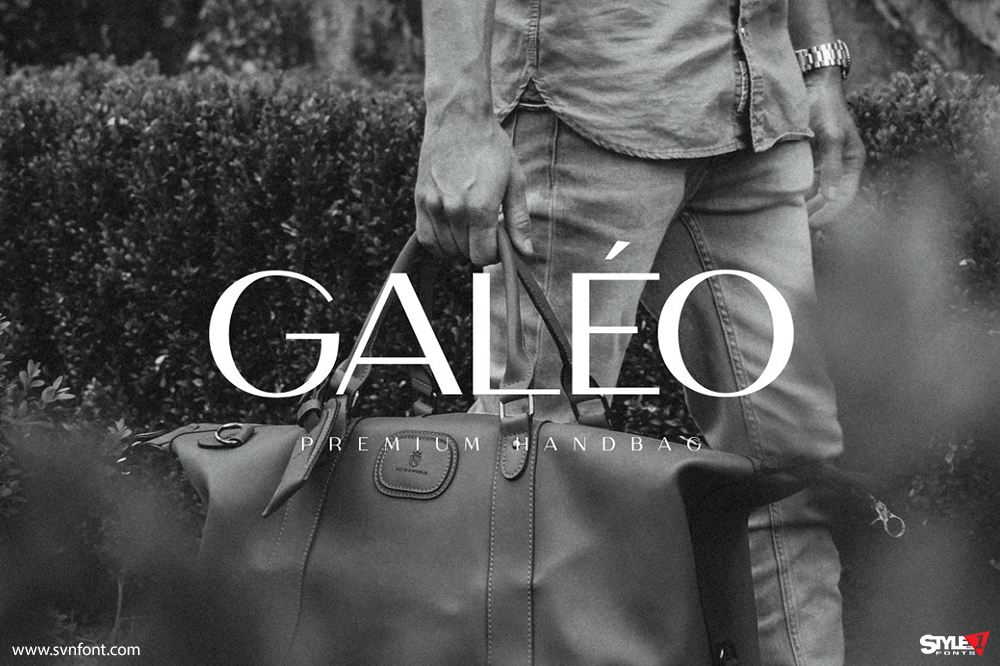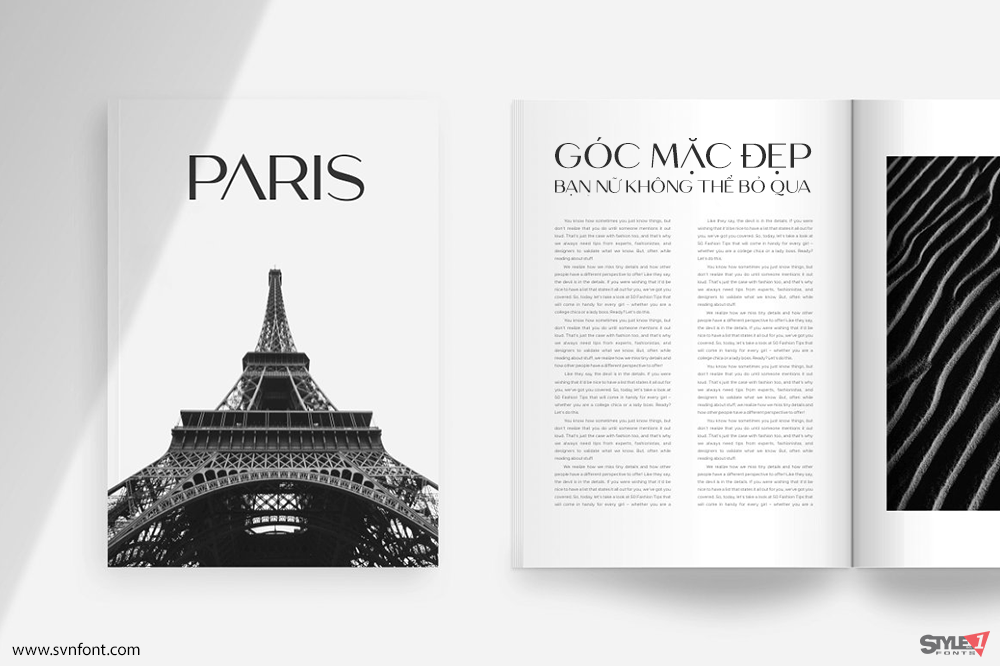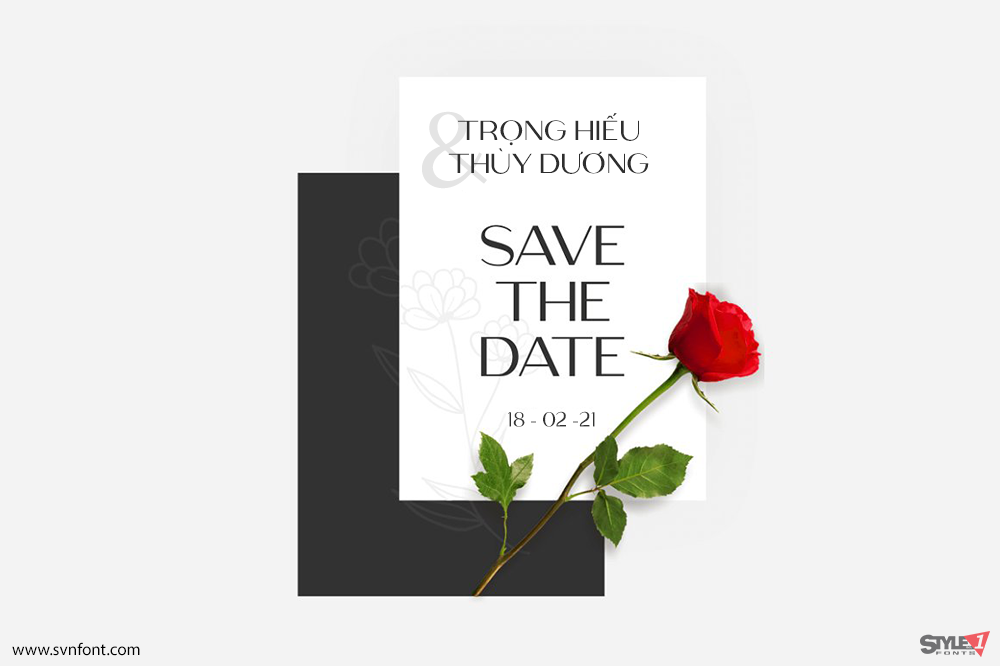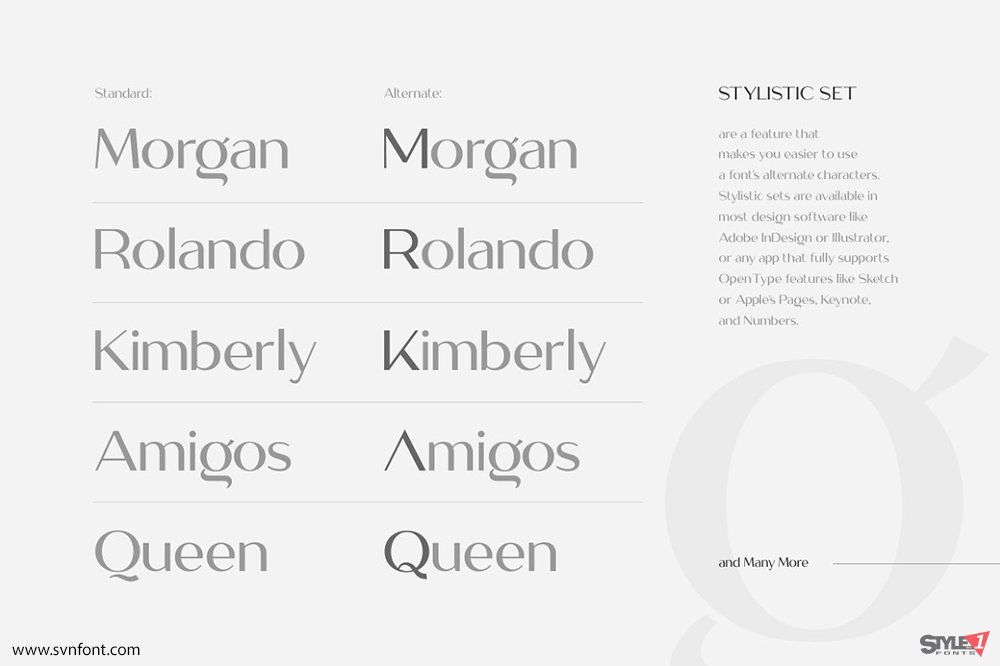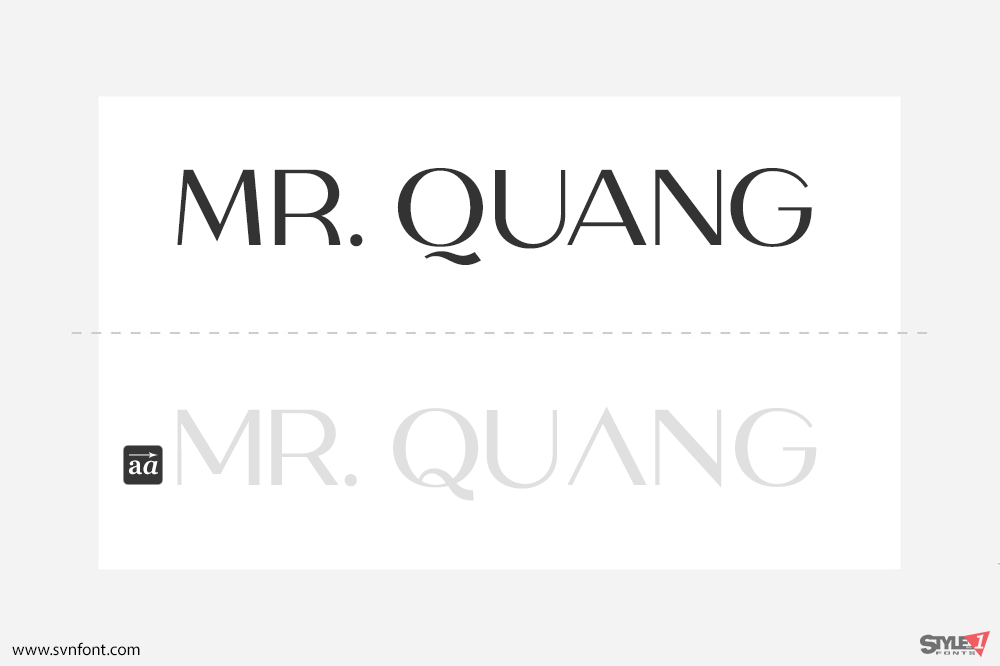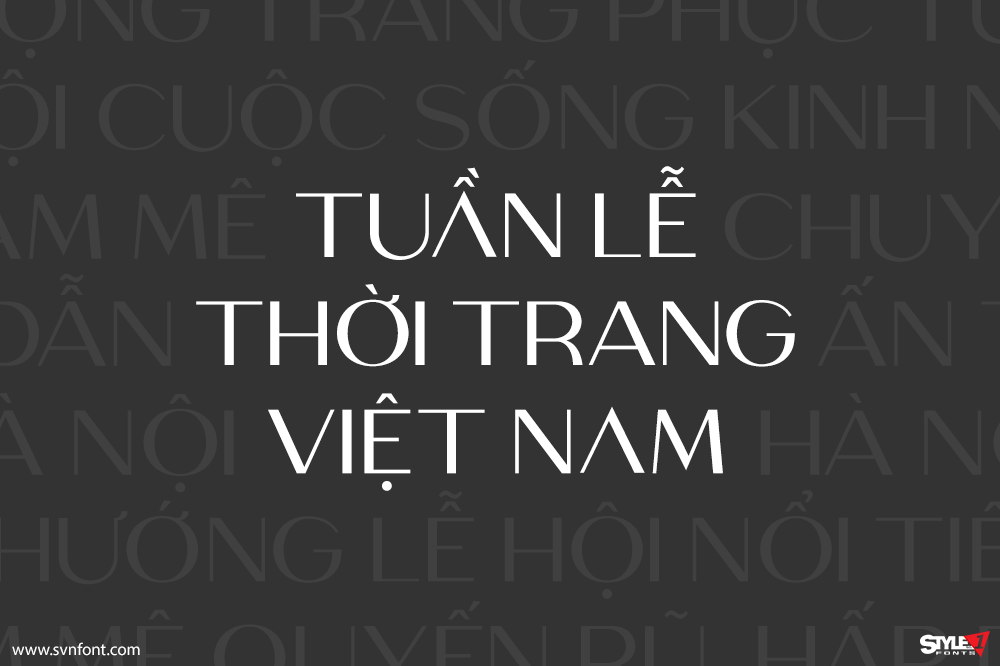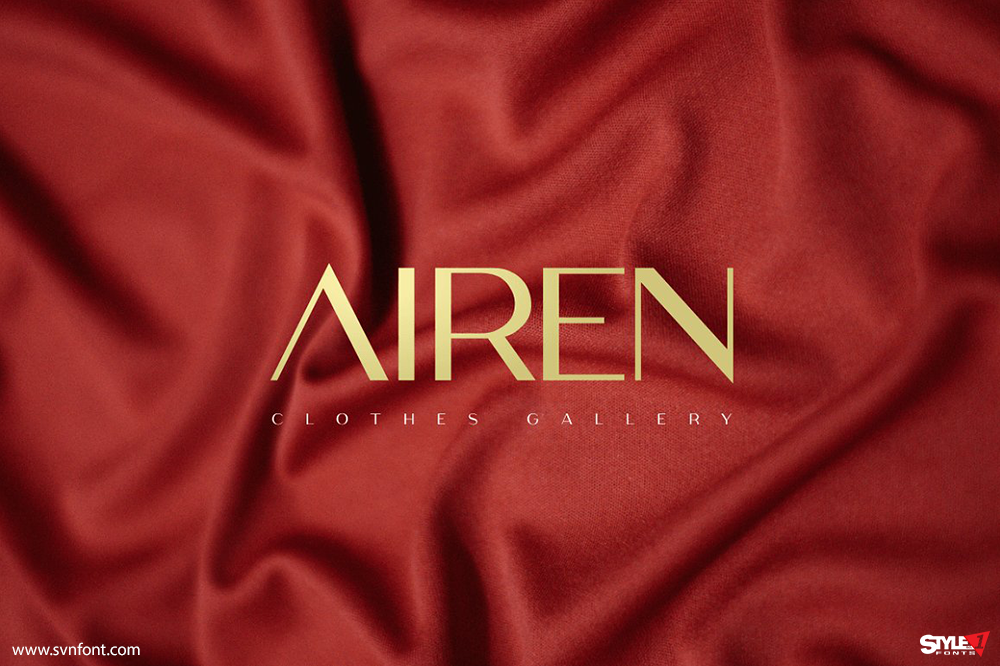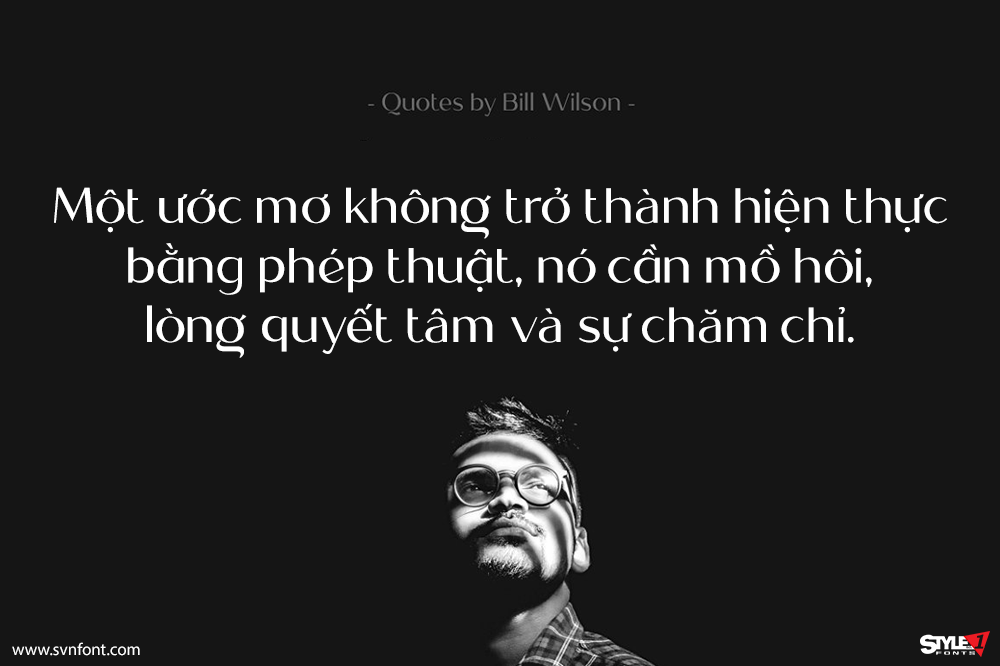
Meganté là một font chữ thư pháp hiện đại, phong cách thời trang với nét chấm phá casual chic. Font chữ này rất phù hợp cho thiết kế thương hiệu, thiệp cưới, thiệp mời và nhiều dự án khác. Meganté bao gồm đầy đủ bộ chữ hoa và chữ thường tinh tế, chữ số và các ký tự thay thế đa dạng.